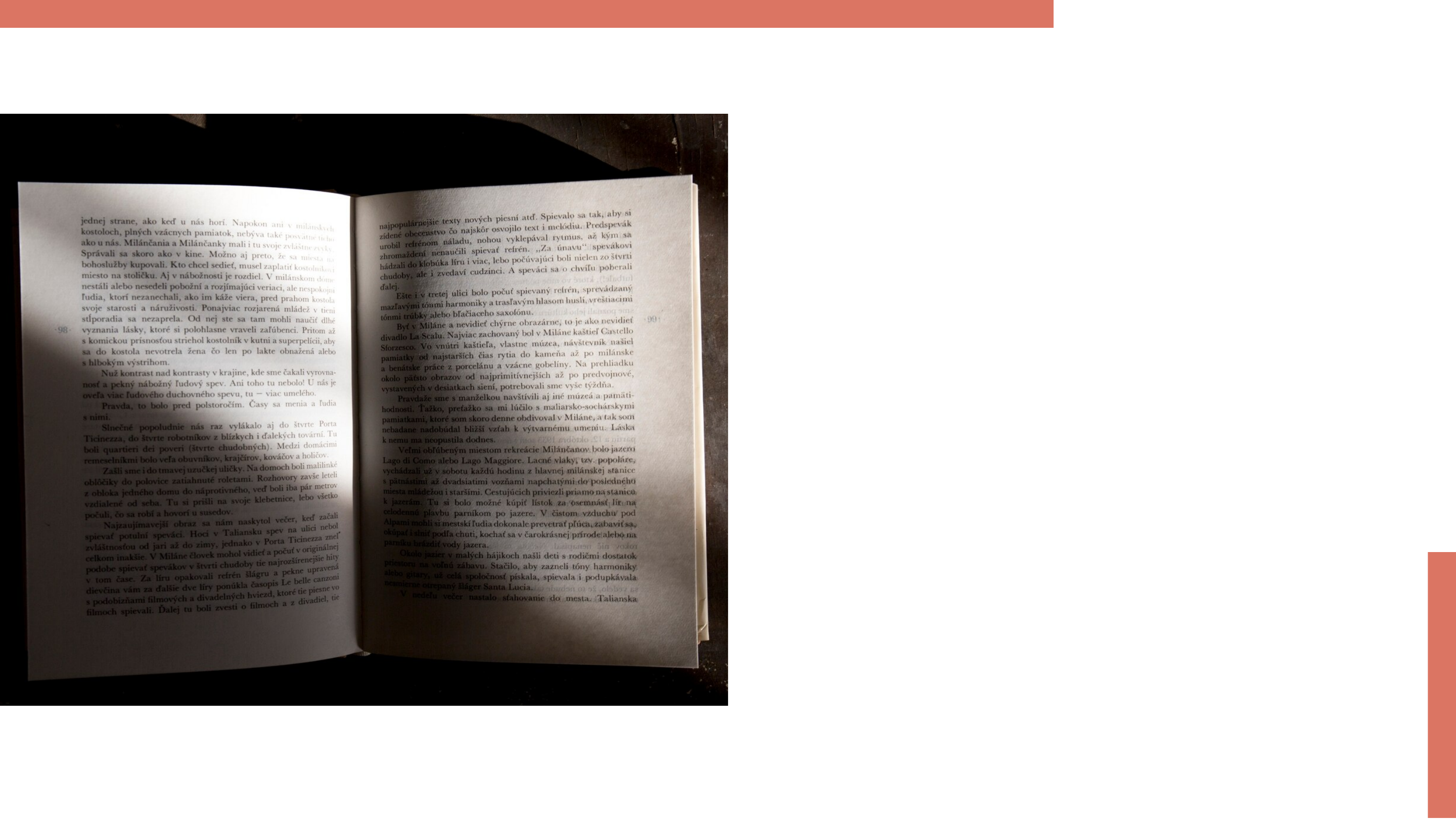
<p>TIPOGRAFIA: A</p><p>ARTE E CIÊNCIA</p><p>DA COMUNICAÇÃO</p><p>VISUAL</p><p>INTRODUÇÃO À TIPOGRAFIA</p><p>Tipografia é a arte e ciência de</p><p>organizar texto. Ela não apenas envolve</p><p>a escolha de fontes, mas também a</p><p>composição e o design do texto para</p><p>facilitar a leitura e a compreensão.</p><p>Vamos explorar como a tipografia</p><p>influencia a comunicação visual.</p><p>A tipografia remonta a séculos atrás,</p><p>com a invenção da prensa de tipos</p><p>móveis por Johannes Gutenberg. Essa</p><p>inovação revolucionou a disseminação</p><p>do conhecimento e a estética da</p><p>impressão, estabelecendo as bases do</p><p>design moderno.</p><p>HISTÓRIA DA TIPOGRAFIA</p><p>Os principais elementos da tipografia</p><p>incluem tipo de letra, tamanho,</p><p>espaçamento e alinhamento. Cada um</p><p>desempenha um papel crucial na</p><p>criação de uma experiência visual</p><p>coesa e agradável ao leitor.</p><p>ELEMENTOS DA TIPOGRAFIA</p><p>CLASSIFICAÇÃO DE FONTES</p><p>As fontes podem ser classificadas em</p><p>serifadas e sans-serif. As serifadas são</p><p>frequentemente vistas como mais</p><p>tradicionais e formais, enquanto as</p><p>sans-serif são mais modernas e limpas.</p><p>A escolha da fonte afeta a percepção</p><p>do texto.</p><p>O espaçamento entre letras, palavras e</p><p>linhas é essencial para a legibilidade.</p><p>Um bom espaçamento melhora a</p><p>fluidez da leitura e mantém o leitor</p><p>engajado. Ajustes finos podem fazer</p><p>uma grande diferença.</p><p>ESPAÇAMENTO E LEGIBILIDADE</p><p>A cor das fontes pode evocar emoções</p><p>e influenciar a compreensão do</p><p>conteúdo. Combinações de cores</p><p>adequadas são fundamentais para</p><p>garantir que o texto seja visível e</p><p>atrativo para o público.</p><p>CORES E TIPOGRAFIA</p><p>No design gráfico, a tipografia é uma</p><p>ferramenta poderosa. Ela pode</p><p>transmitir a personalidade de uma</p><p>marca e criar hierarquia visual. Um bom</p><p>designer utiliza a tipografia para guiar</p><p>o olhar do espectador.</p><p>A TIPOGRAFIA NO DESIGN</p><p>GRÁFICO</p><p>Evitar erros comuns, como o uso</p><p>excessivo de fontes ou má escolha de</p><p>espaçamentos, é crucial. Esses erros</p><p>podem comprometer a eficácia da</p><p>comunicação e causar distrações ao</p><p>leitor.</p><p>ERROS COMUNS EM</p><p>TIPOGRAFIA</p><p>TIPOGRAFIA DIGITAL</p><p>Com o avanço da tecnologia, a</p><p>tipografia digital tornou-se</p><p>predominante. Novas fontes e estilos</p><p>estão sempre surgindo, permitindo que</p><p>os designers experimentem e criem</p><p>experiências interativas únicas.</p><p>TENDÊNCIAS EM TIPOGRAFIA</p><p>As tendências em tipografia estão</p><p>sempre mudando. Atualmente, vemos</p><p>um aumento no uso de fontes</p><p>personalizadas e variáveis. Essas</p><p>inovações oferecem mais flexibilidade e</p><p>criatividade no design.</p><p>IMPACTO DA TIPOGRAFIA</p><p>A tipografia tem um impacto profundo</p><p>na comunicação visual. Ela pode</p><p>influenciar a percepção da marca e a</p><p>experiência do usuário, tornando-se um</p><p>elemento essencial em qualquer projeto</p><p>de design.</p><p>CONCLUSÃO</p><p>A tipografia é uma combinação de arte e ciência, essencial para a</p><p>comunicação visual eficaz. Ao dominar seus princípios, designers</p><p>podem criar experiências memoráveis e impactantes que ressoam</p><p>com o público.</p>